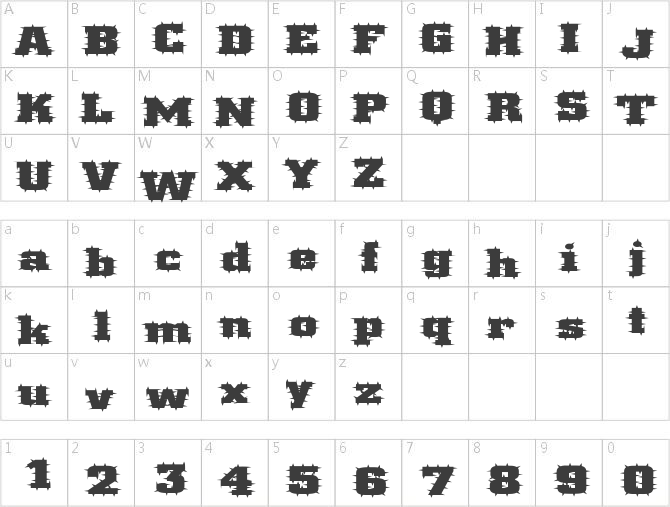
FZ BASIC 53 SPIKED EX 詳情頁(yè)
FZ BASIC 53 SPIKED EX字體字庫(kù)是一款讓人賞心悅目、百看不厭的英文字體,適合各類(lèi)廣告和產(chǎn)品包裝設(shè)計(jì)應(yīng)用,字體大小0.08MB,格式為ttf字體,上傳用戶(hù)是happy,作者/版權(quán)方為未知